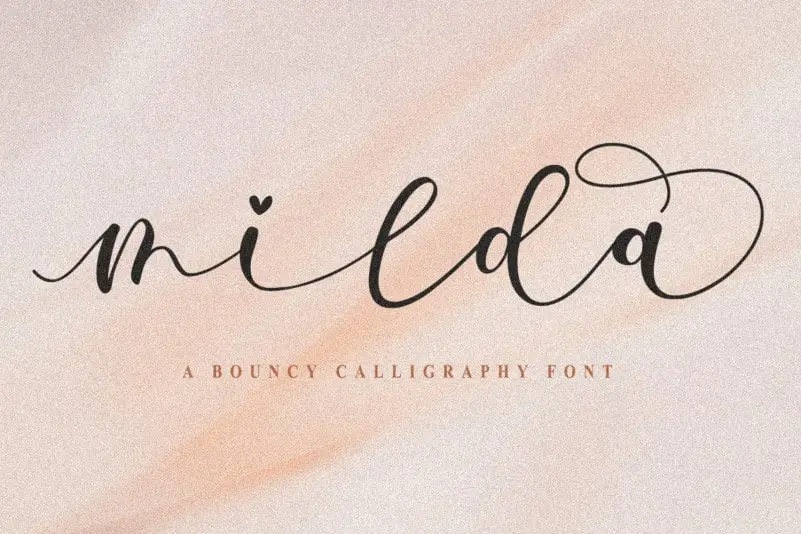
Milda – A Bouncy Calligraphy Font – Fonte Grátis
Milda - A Bouncy Calligraphy Font
A Milda é uma elegante e suavemente vibrante tipografia calligrafia que se destaca para projetos luxuosos. Suas linhas curvas e fluidas permitem uma execução única, tornando-a um recurso indispensável para qualquer projeto de alta qualidade, desde convites de casamento até logomarcas sofisticadas ou cartões de encorajamento. Com sua aparência arredondada e vibrante, a Milda é especialmente adequada para dar vida a uma variedade de projetos, incluindo cartazes nas mídias sociais, embalagens de produtos, e até mesmo citações impressas em materiais finos ou delicados. O resultado? Textos atraentes que brilham em qualquer meio, criando um impacto imediato e elegante. A Milda é uma escolha perfeita para quem busca um charme único e sofisticado em seus projetos de design.